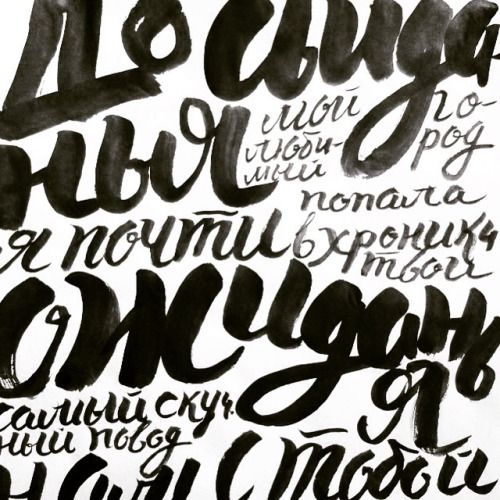
Как создать шрифт с нуля
Предисловие
Сосредоточьтесь на мелочах, даже если они сделаны не очень хорошо, делайте это от души, создавая красивую систему сеток, создавая угол шрифта и делая дизайн красивым благодаря деталям …
Давайте посмотрим на мои предыдущие варианты дизайна:
Как создать шрифт с нуля
Многие студенты, которые плохо знакомы с дизайном шрифтов, часто сталкиваются с ситуацией, когда их идеи высоки, а результат очень печален. Почему такой результат? В конечном счете, если вы недостаточно знаете о самом дизайне шрифтов, просто следуйте за тыквой и нарисуйте ее напрямую. Чтобы избежать этого неприятного результата, мы должны провести различные приготовления перед тем, как приступить к созданию шрифтов, и постоянно искать отличный дизайн шрифтов. Ищите ощущение дизайна, установите сетку после подтверждения ощущения и начинайте создавать шрифты постепенно. Когда я занимаюсь дизайном шрифта, я буду следовать нескольким шагам: «построить сетку» — «выбрать шрифт» — «разобрать шрифт» — «мазки краски» — «связать каркас» — «толщина и тонкость» — «выбрать и выбросить» — » отшлифовать детали »-« пощупать ».
Давайте возьмем самый распространенный матричный шрифт в качестве примера, чтобы поделиться с вами, как создавать шрифты.
1. Построение сетки: создайте систему сеток и создайте сплошной шрифт на земле Это неотделимо от спецификаций системы сетки.
2. Удаление шрифта: возьмите «прожечь» в качестве примера — выберите шрифт по умолчанию и разделите штрихи в соответствии со структурой шрифта.
3. Рисование штрихов: используйте горизонтальные и вертикальные линии, чтобы перерисовать разделенные штрихи в системе сетки. Не делайте подробностей в данный момент. Пропуски и точки также классифицируются как горизонтальные и вертикальные линии в соответствии с их собственным направлением и структурными характеристиками.
4. Свяжите скелет: штрихи шрифта, нарисованные путем разделения, являются костями шрифта. Соединения между штрихами можно понимать как суставы человеческого тела. Назначение суставов заключается в обеспечении стабильности и гибкости шрифта.
Штрихи шрифта могут быть основаны на потребности Vision в перемещении суставов в определенном диапазоне, а также можно отрегулировать соотношение длины.
5. Толщина и четкость. Толщина и твердость штрихов определяются темпераментом шрифта, который вам нужен. Мелкие и изогнутые штрихи мягкие и красивые, а толстые и прямые штрихи спокойны и атмосферны. Хотя дизайн это чувство, это чувство для начала Ученым трудно контролировать, поэтому я поделюсь с вами толщиной нескольких часто используемых штрихов. На доске для рисования 1000PX * 1000PX используйте 6 пикселей, 10 пикселей и 20 пикселей в качестве основного штриха. толщину, причем выбирать можно по желаемому деловому темпераменту;
6. Деконструкция и построение: общие структуры шрифтов включают «верхнюю и нижнюю структуру», «верхнюю, среднюю и нижнюю структуру», «левую и правую структуру», «левую, центральную и правую структуру», «полузамкнутую структуру» и «полностью закрытая конструкция». Среди них «структура вверх и вниз» подчеркивает относительно небольшую часть штрихов, тем самым достигая баланса самого шрифта.
7. Выбор и выбор: после того, как штрихи станут толще, соотношение расстояния между штрихами всего шрифта будет в определенной степени изменено. Поэтому для эстетики и воздухопроницаемости шрифта мы сделаем некоторые варианты и интеграции структура шрифта
8. Полировка деталей. Чтобы шрифт выглядел более комфортно, мы скругляем углы шрифта и регулируем угол круга в соответствии с сеткой.
9. Чтобы почувствовать: отшлифуйте общий шрифт и продолжайте изображать детали.
нота:
В группе символов структура каждого отдельного символа различна.
Важно поддерживать постоянный визуальный размер, соответствующим образом регулируя внутренние пропорции шрифта, чтобы сформировать удобный жест для органов чувств. Существует много типов шрифтов с китайскими иероглифами, но если мы используем геометрические правила для разделения типов шрифтов, их можно грубо разделить на четыре типа: квадрат, круг и треугольник. С точки зрения площади, квадрат и круг имеют наибольшую площадь. по треугольнику, поэтому мы хотим сохранить. Согласованность больших и маленьких символов должна регулировать соотношение размеров между ними, чтобы размер был однородным, штрихи согласованными, структура была строгой, а промежутки были умеренными.
Чтобы подчеркнуть темперамент шрифта, шрифт обычно делают слегка тонким и длинным.
Существует много типов методов дизайна шрифтов. У каждого дизайнера есть своя собственная точка входа, и конечный результат — это то, что он хочет. Вышеупомянутый обмен надеется немного помочь новичкам в дизайне шрифтов и приветствовать всех коллег.
Шрифт. 7-й класс
Цель: Изучение понятия «шрифт».
Задачи:
- Знакомство с эволюцией письменности.
- Развитие культуры изображения и творческого воображения.
- Формирование художественного вкуса, воспитание эстетического отношения к искусству шрифта.
Тема нашего урока – «Шрифт». Сегодня мы должны с вами ознакомиться с понятием «шрифт» и историей его развития.
Что мы понимаем под шрифтами? Это своеобразные письменные знаки, передающие определённую информацию.
Где в нашей жизни мы их можем встретить? Шрифты окружают нас повсюду: книги, газеты, журналы, объявления, буклеты, билеты различного назначения /кино, театр, лотерея и др.